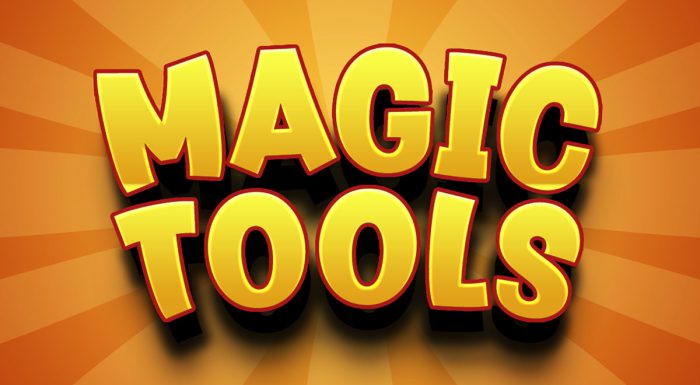
فونت Magic Tools انگلیسی
| ⭐ توضیحات | Magic Tools یک فونت نمایشی پررنگ و بازیگوش است. با این فونت دوست داشتنی تایپوگرافی چشم نوازی ایجاد کنید که در مواد تبلیغاتی، پوسترها، بنرها، سرفصل ها، برنامه ها، وب سایت ها و بسیاری موارد دیگر عالی به نظر می رسد! |